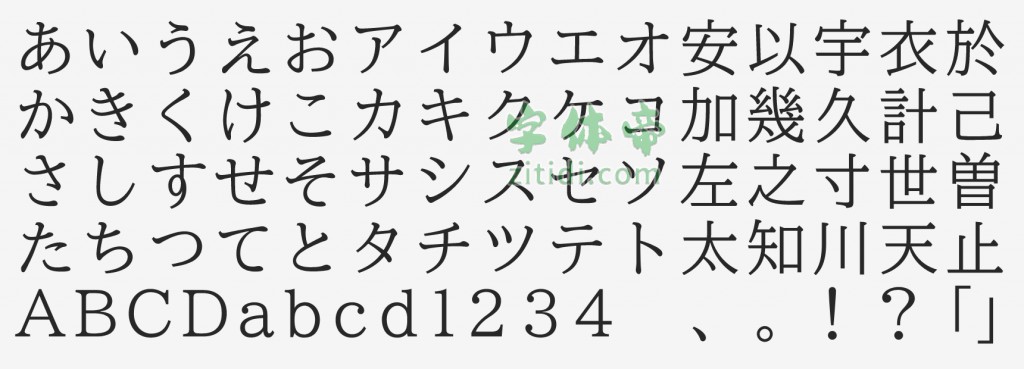
森泽 UD 明朝结合了易于识别和易读性以及 Mincho 字体的高级传统。由于大多数 Mincho 类型的设计都带有精细的水平线条,因此某些显示和标志对于有视力问题的人来说难以阅读。“TypeBank UD Mincho”是在“TypeBank Yoko Futo (Bold Horizontal) Mincho”的基础上设计的,水平线条比传统的 Mincho 字体更粗。对于通用设计版本,响音和半响音符号设计用于更容易识别,并且调整了字符以保持其形状,具有略大的字面和更宽的中宫。